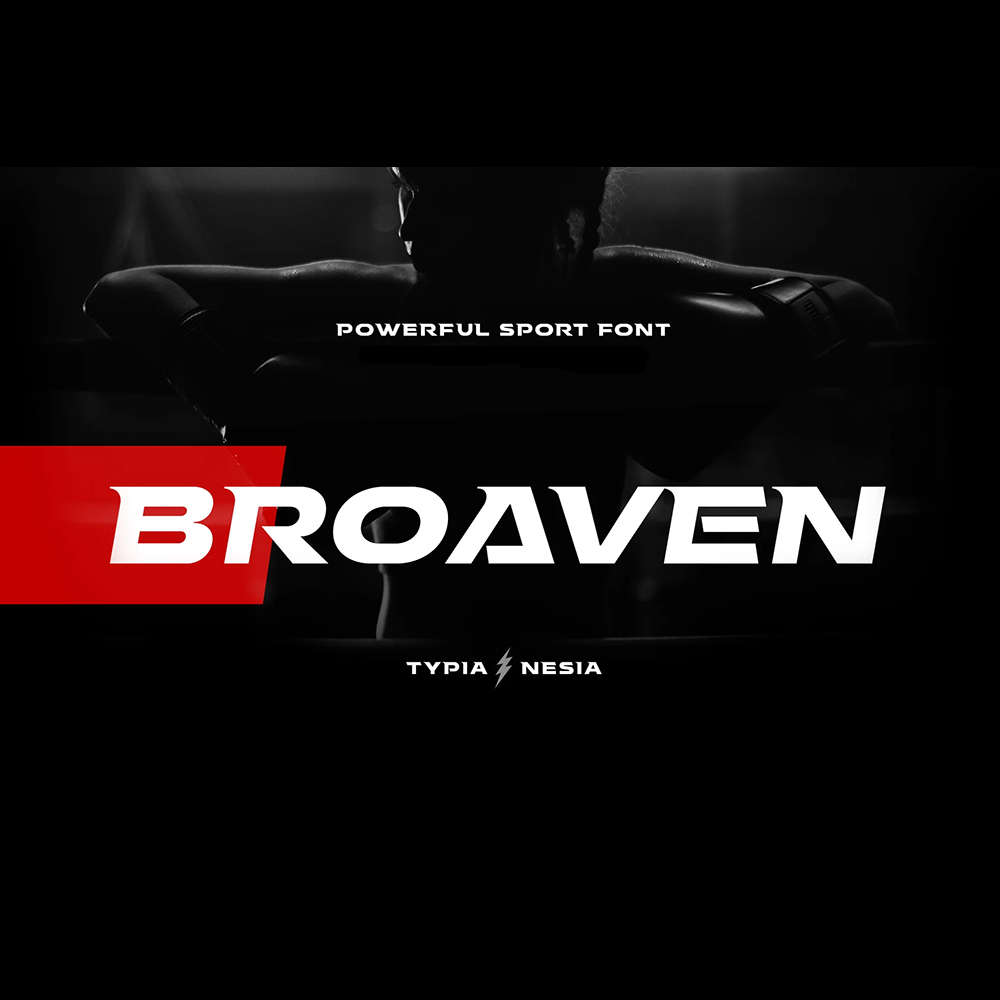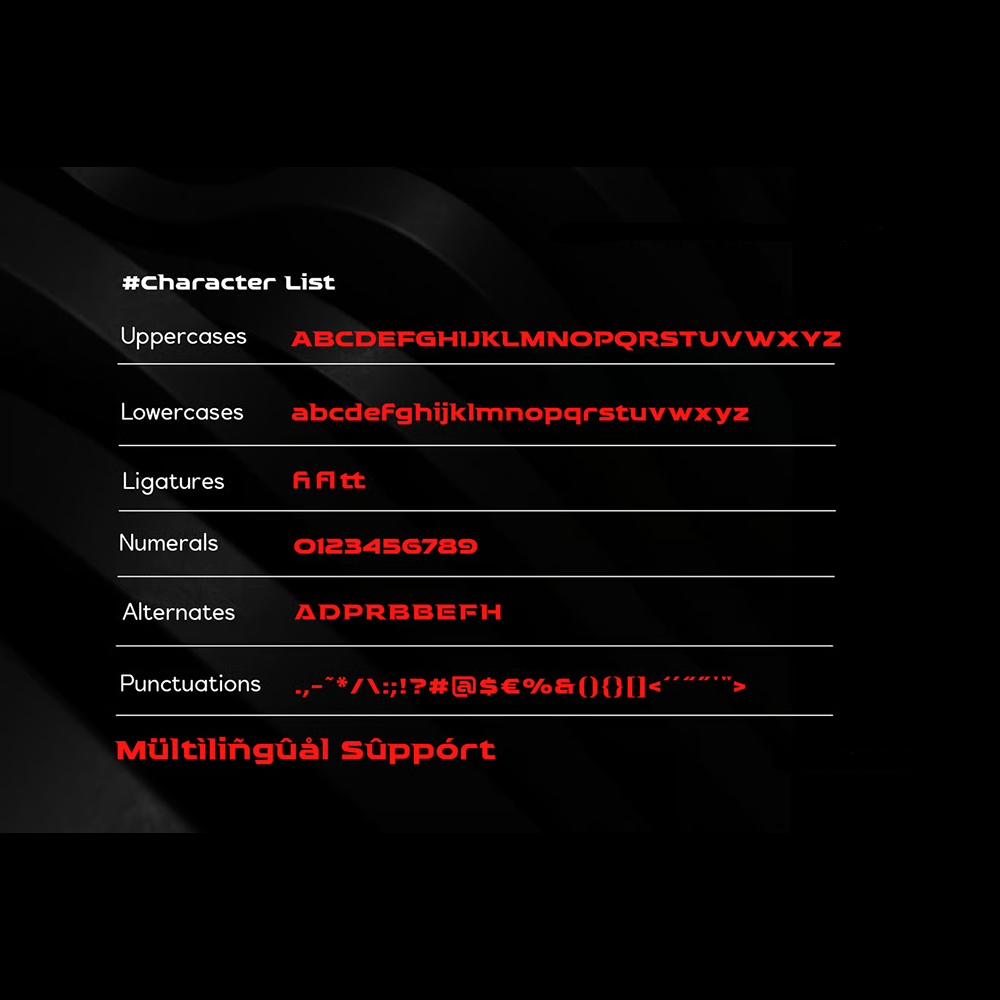
دانلود فونت انگلیسی Broaven Font
فونت پرمیوم و انگلیسی Broaven یک فونت نمایشی پررنگ و توسعهیافته است. فونت ورزشی Broaven مناسب لوگو، طراحی سرمقاله، برندسازی باشگاه تناسب اندام، صنعت بازی، مسابقات…
فونت پرمیوم و انگلیسی Broaven یک فونت نمایشی پررنگ و توسعهیافته است. فونت ورزشی Broaven مناسب لوگو، طراحی سرمقاله، برندسازی باشگاه تناسب اندام، صنعت بازی، مسابقات ورزشی، سوپراسپرتها، برندسازی ورزشهای الکترونیکی، پوسترهای موسیقی، طراحی وبسایت، طراحی تبلیغات مدرن، نقل قولهای پوستر، عناوین کتاب/جلد، رویدادهای ویژه و موارد دیگر میباشد.
مزایای استفاده از فونت لاتین Broaven Font چیست؟